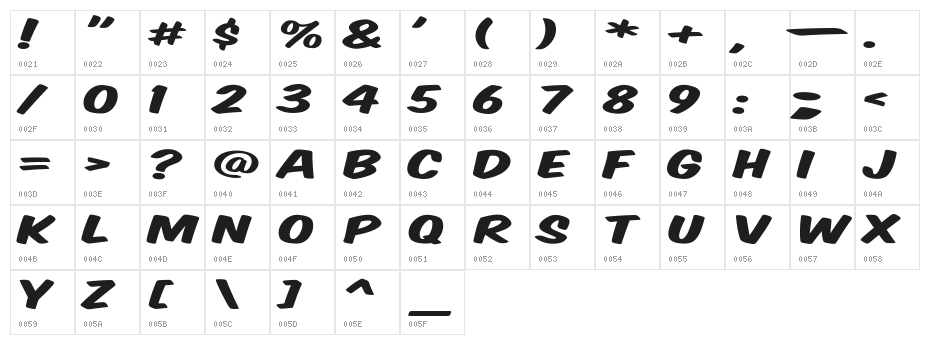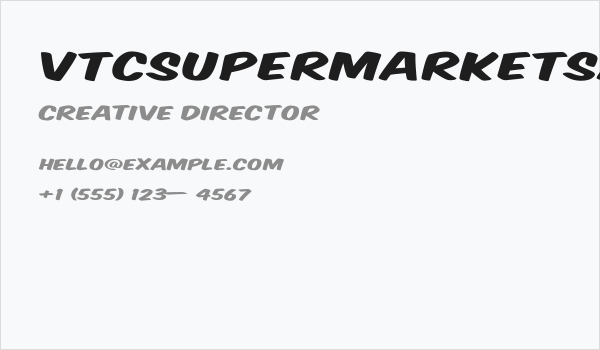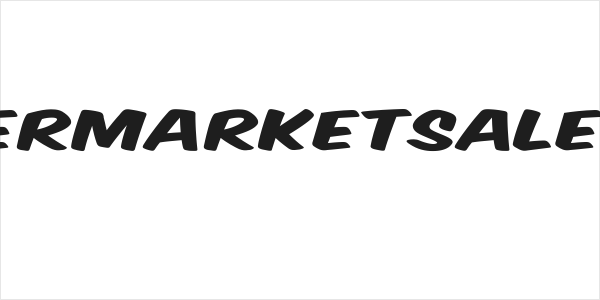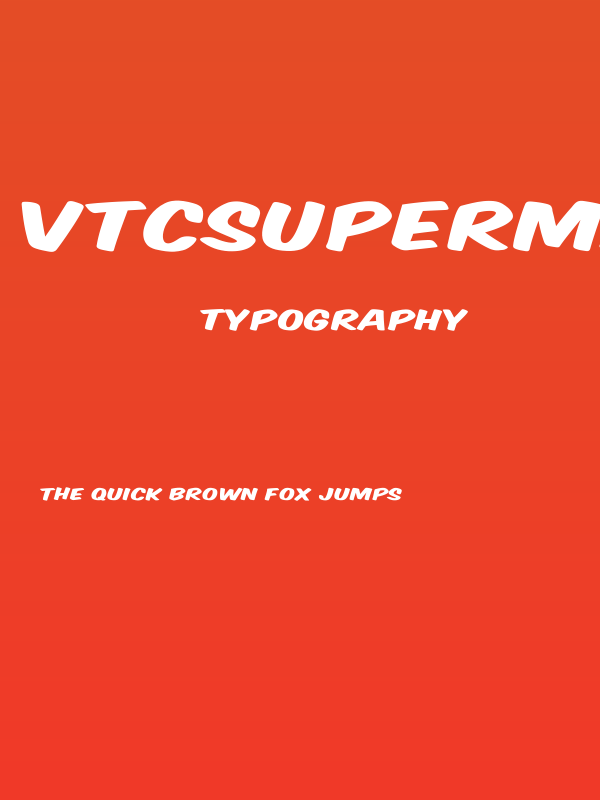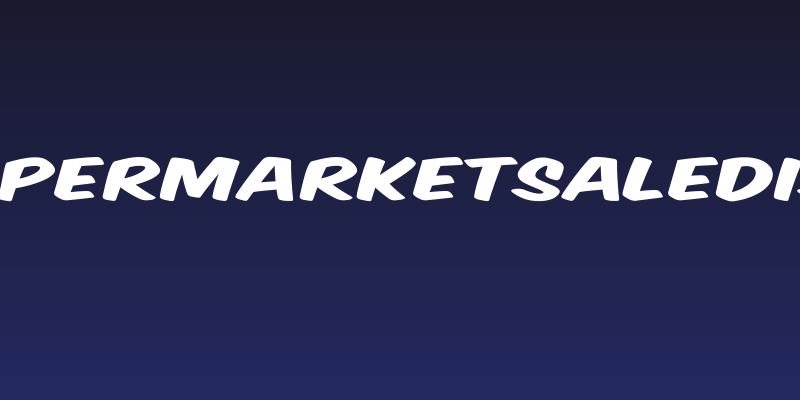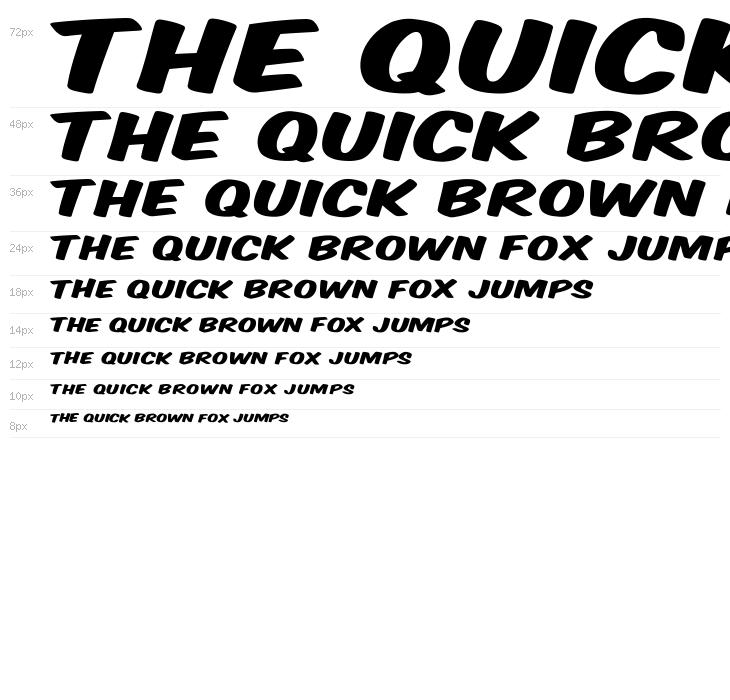
VTCSuperMarketSaleDisplay Font
✎ Round
| Anwendungsfall | Headlines, Promotional materials |
| Vorgeschlagene Projekte | Ideal for promotional materials, advertisements, and headlines that require a bold and energetic look. |